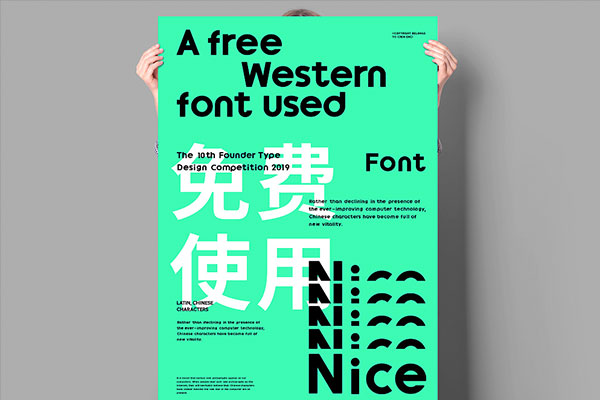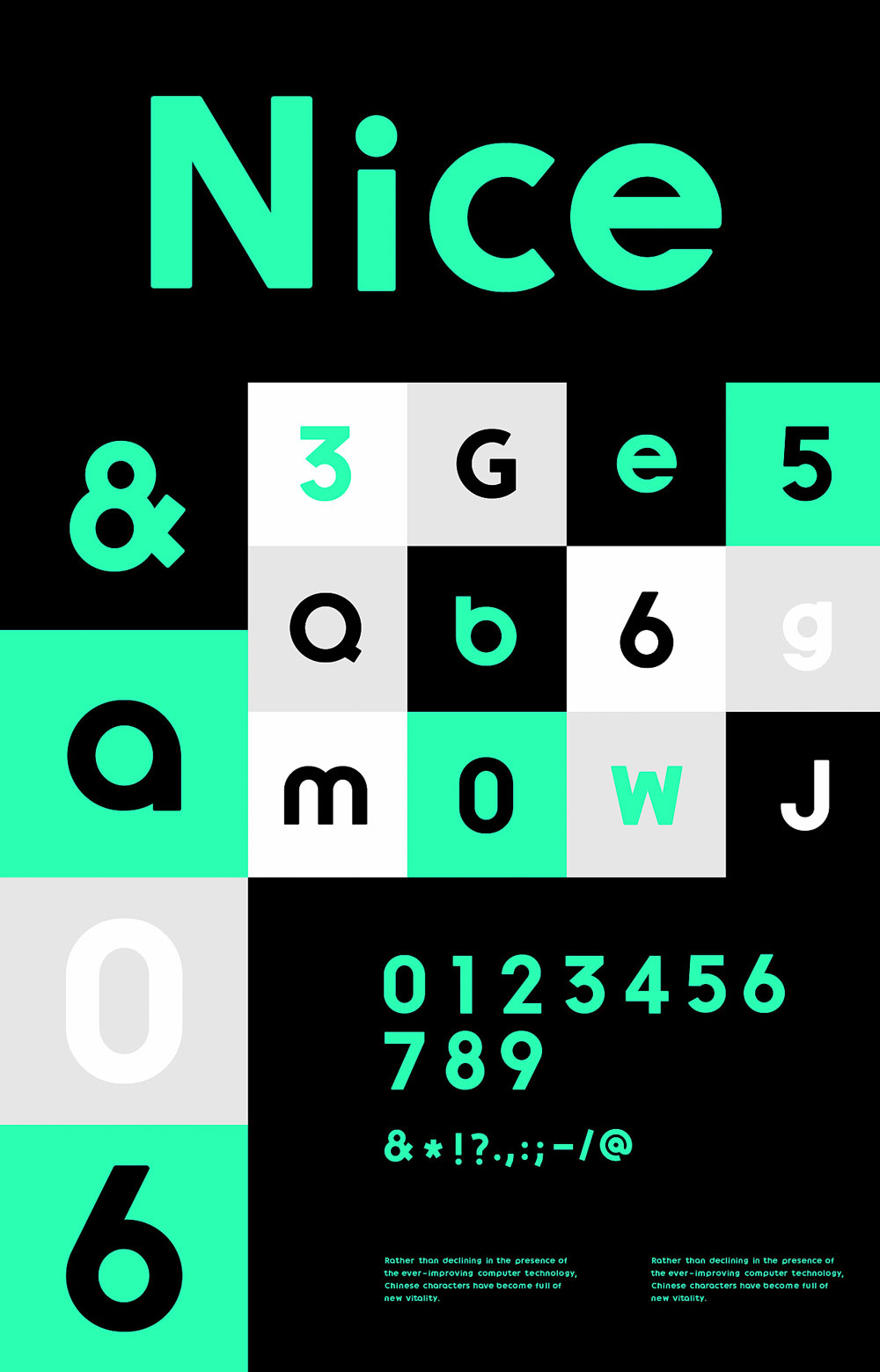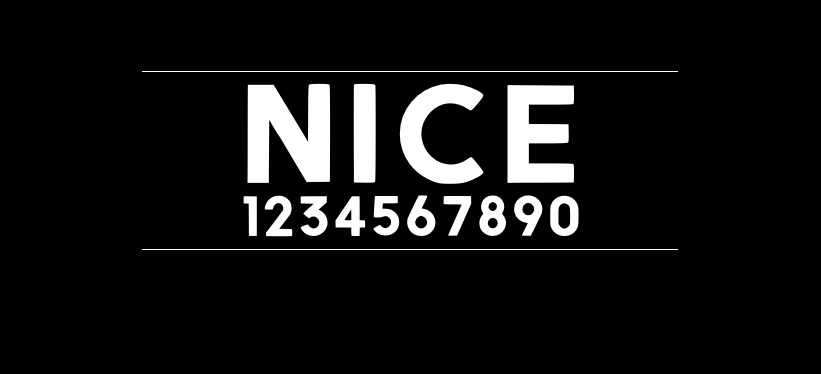
Nice
Nice是厦门的设计师设大叔创作的一款免费商用字体,这是一款无衬线西文字体,据作者介绍是19年参加方正字体大赛的作品,虽未能获奖,但作者觉得这款字作为标题来使用是非常不错的,一直想做成字库,一直到现在才整理出来,免费供各位使用。
Nice生成字库后小写有一点小Bug,对齐稍微有点小问题,不过影响不大,大写比较完整,作为标题使用是非常不错的。
Nice包含Nice Regular和NiceBold两个字重,提供了ttf和otf两种格式。